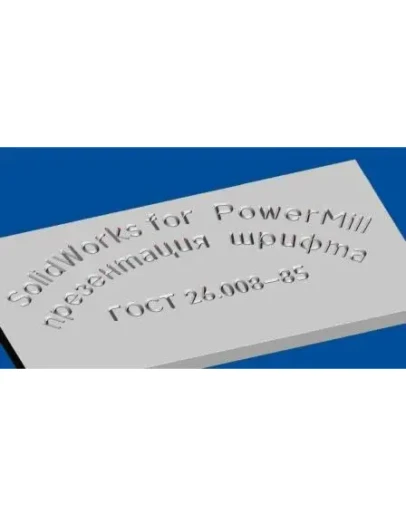
Шрифт разрабатывался под SolidWorks (возможно использование других CAD применяющих
системные шрифты) для последующего экспорта шаблона траектории в формате DXF в CAM
(например PowerMill)
ГОСТ 26.008-85 Пр3 шрифт true-tupe для гравировки по ср